Trong xu hướng thiết kế vintage và retro, những kiểu chữ mang hơi hướng hoài cổ ngày càng được nhiều designer và doanh nghiệp lựa chọn để tạo dấu ấn khác biệt cho thương hiệu. Từ poster, menu, tem nhãn đến bao bì sản phẩm, một bộ font phù hợp có thể góp phần truyền tải câu chuyện và cá tính của thiết kế ngay từ cái nhìn đầu tiên. Nếu bạn đang tìm kiếm font chữ Typewriter Việt hóa đẹp, dễ sử dụng và phù hợp cho cả thiết kế kỹ thuật số lẫn in ấn, bài viết này sẽ tổng hợp những bộ font nổi bật kèm gợi ý ứng dụng thực tế. Bên cạnh đó, Bao Bì Asia cũng chia sẻ một số kinh nghiệm lựa chọn và kết hợp font để giúp các ấn phẩm in như hộp giấy, túi giấy hay nhãn dán bao bì đạt hiệu quả thẩm mỹ và khả năng nhận diện thương hiệu tốt hơn.
Font chữ Typewriter là gì?
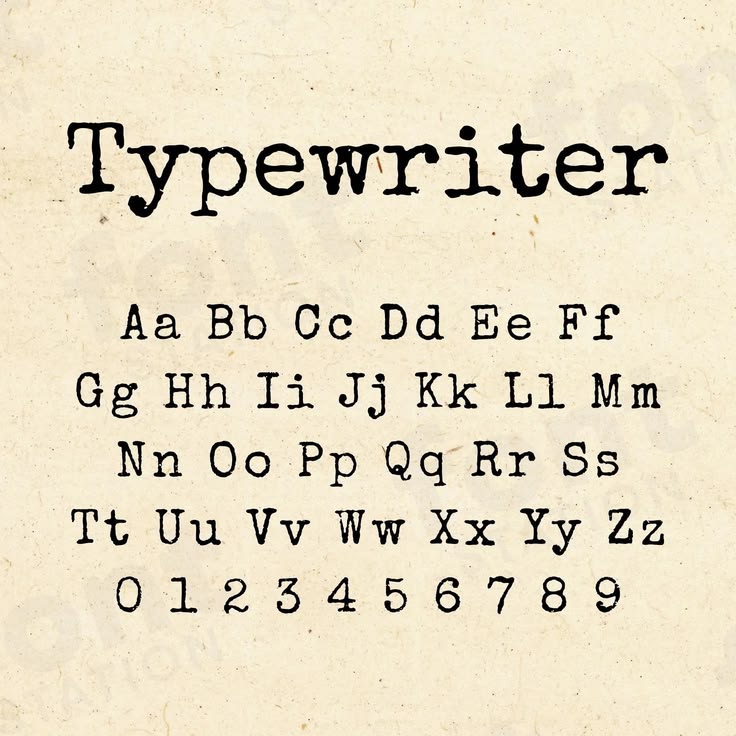
Font chữ Typewriter
Font chữ Typewriter (hay còn gọi là font máy đánh chữ, font chữ đánh máy ngày xưa) là nhóm kiểu chữ mô phỏng các ký tự được tạo ra từ máy đánh chữ cơ học. Đặc trưng của font là nét chữ đơn giản, khoảng cách ký tự đều và mang đậm phong cách cổ điển, tạo cảm giác hoài niệm cho các thiết kế.
Ngày nay, font Typewriter được ứng dụng rộng rãi trong thiết kế poster, bìa sách, bao bì, menu, thiệp và nhiều ấn phẩm truyền thông. Bên cạnh các font kinh điển, hiện nay cũng có nhiều font Typewriter Việt hóa hỗ trợ đầy đủ dấu tiếng Việt, giúp designer và doanh nghiệp dễ dàng sử dụng trong các dự án thiết kế và in ấn.
Tổng hợp 10+ font chữ Typewriter Việt hóa đẹp, miễn phí tải về
Nếu bạn đang tìm kiếm font Typewriter Việt hóa miễn phí để thiết kế poster, bao bì, menu hay các ấn phẩm mang phong cách vintage, dưới đây là những font đơn cách hỗ trợ tiếng Việt, được sử dụng miễn phí và phù hợp cho nhiều mục đích thiết kế.
Font Typewriter phong cách cổ điển, retro
- VT323: Lấy cảm hứng từ màn hình máy tính và máy đánh chữ điện tử thập niên 80, phù hợp với các thiết kế retro, pixel và poster hoài cổ.
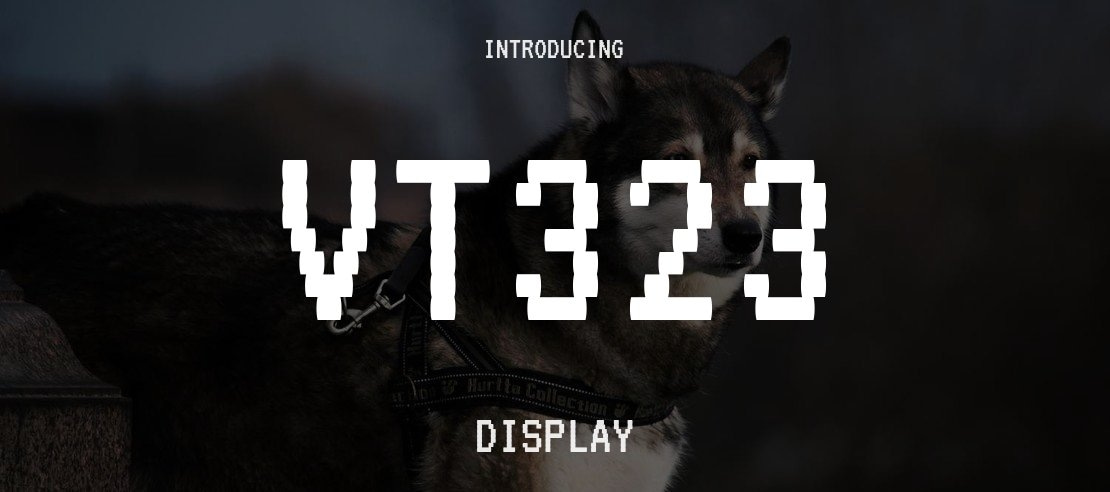
VT323
- Space Mono: Sở hữu nét chữ hơi lệch tự nhiên, mang đậm phong cách máy đánh chữ cổ nhưng vẫn hiện đại, thích hợp cho tiêu đề và ấn phẩm sáng tạo.
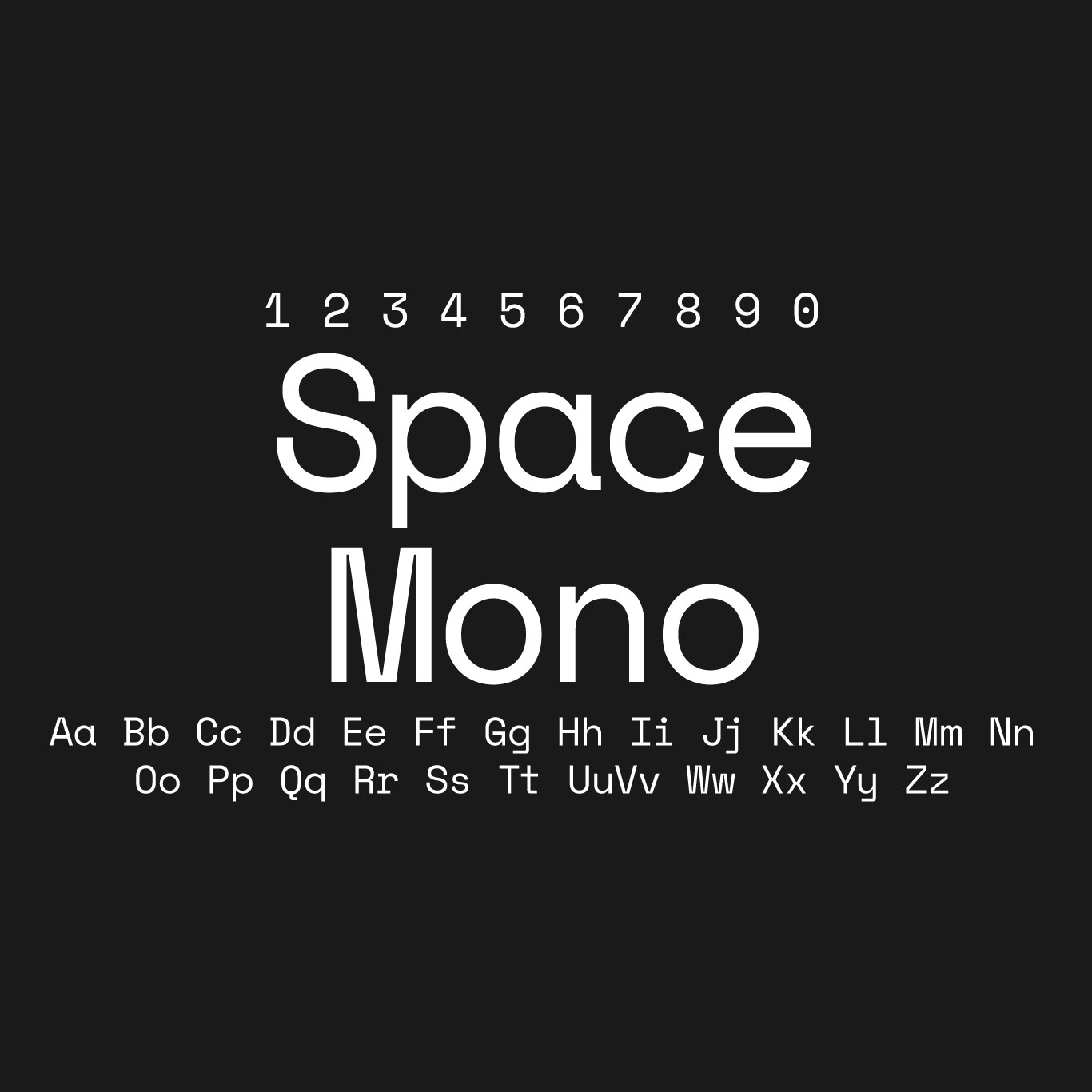
Space Mono
- Cousine: Mô phỏng kiểu chữ Courier truyền thống với các ký tự cân đối, phù hợp cho tài liệu, menu và thiết kế theo phong cách cổ điển.
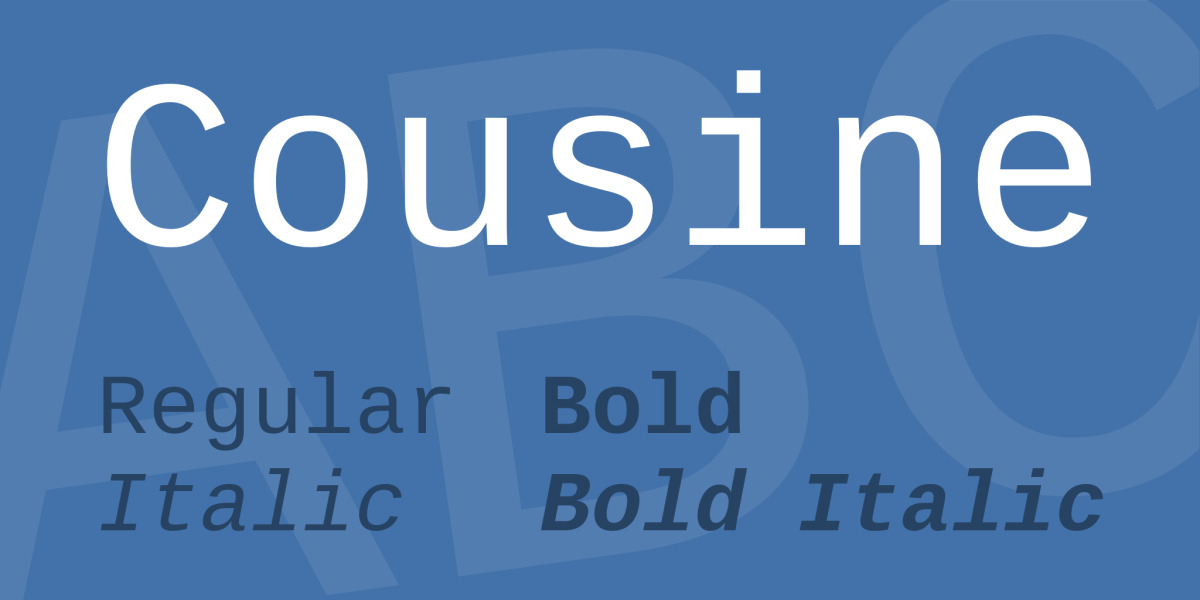
Cousine
- Xanh Mono: Font monospace do người Việt phát triển, hỗ trợ đầy đủ dấu tiếng Việt, thích hợp cho cả nội dung và tiêu đề.
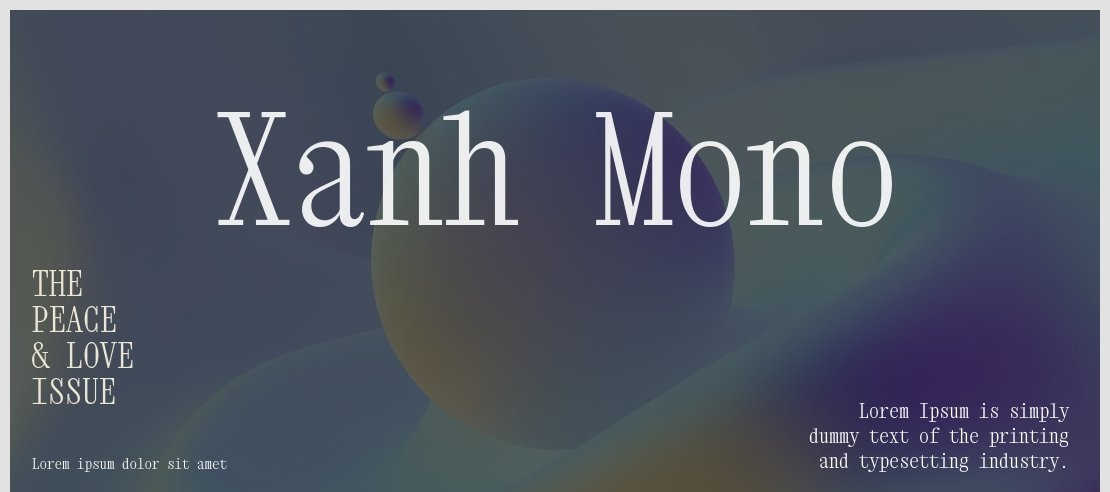
Xanh Mono
- Chivo Mono: Thiết kế vuông vức, khỏe khoắn với hơi hướng retro, phù hợp cho poster, banner và bao bì vintage.
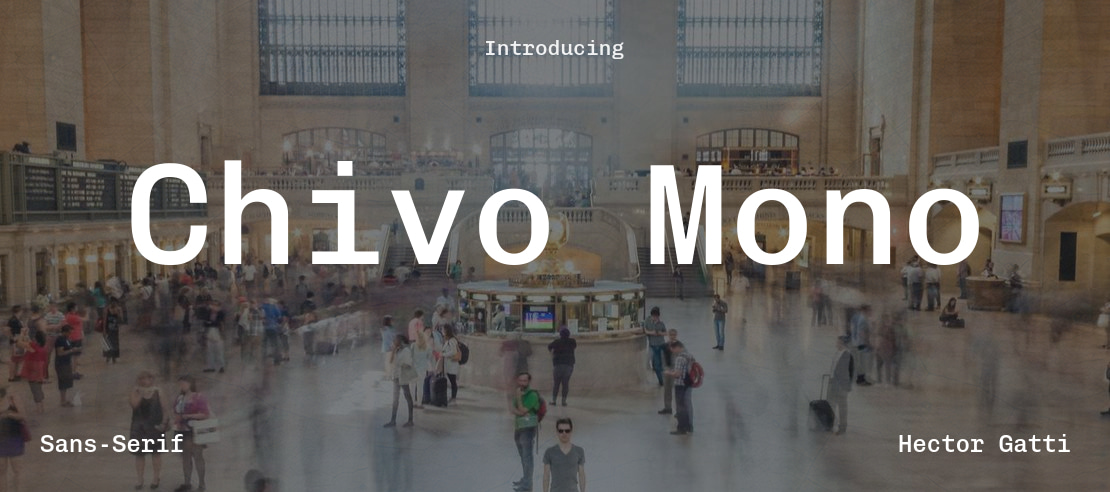
Chivo Mono
- Major Mono Display: Font có cá tính mạnh với toàn bộ ký tự viết hoa, thường được dùng cho logo, tiêu đề hoặc các thiết kế cần tạo điểm nhấn.
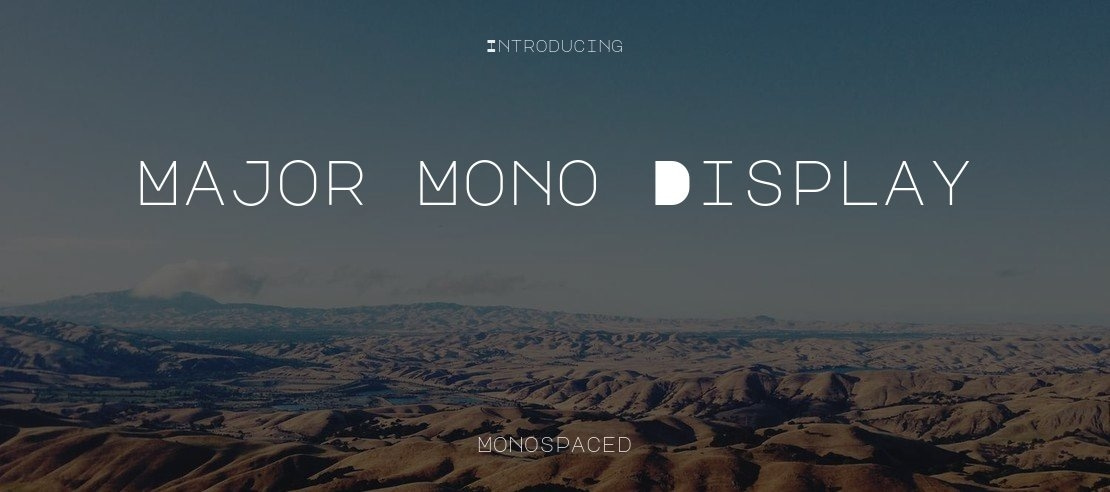
Major Mono Display
Font Mono hiện đại, dễ đọc
- IBM Plex Mono: Thiết kế bởi IBM với kiểu chữ rõ ràng, cân đối, phù hợp cho cả văn bản dài và các thiết kế mang phong cách máy đánh chữ hiện đại.
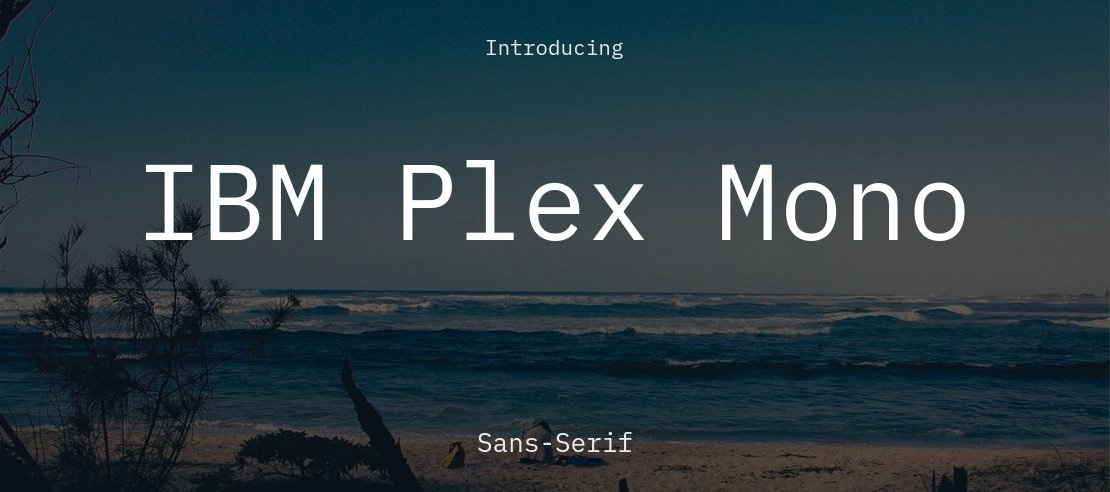
IBM Plex Mono
- JetBrains Mono: Font đơn cách hiện đại, hiển thị sắc nét và dễ đọc, phù hợp cho giao diện, tài liệu hoặc thiết kế tối giản.
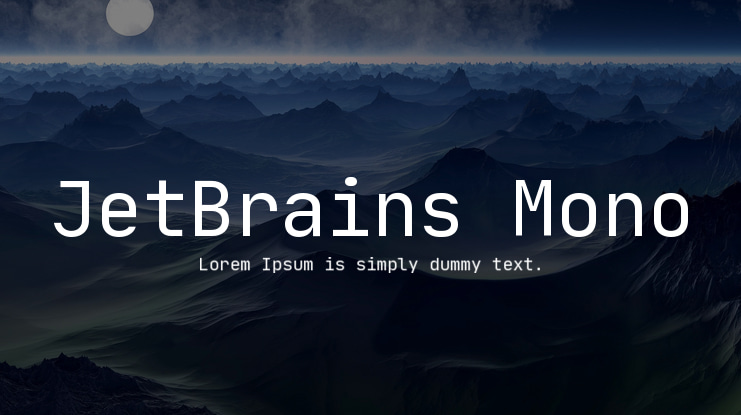
JetBrains Mono
- Source Code Pro: Font miễn phí của Adobe với khoảng cách ký tự hợp lý, thích hợp cho các ấn phẩm cần sự gọn gàng và chuyên nghiệp.
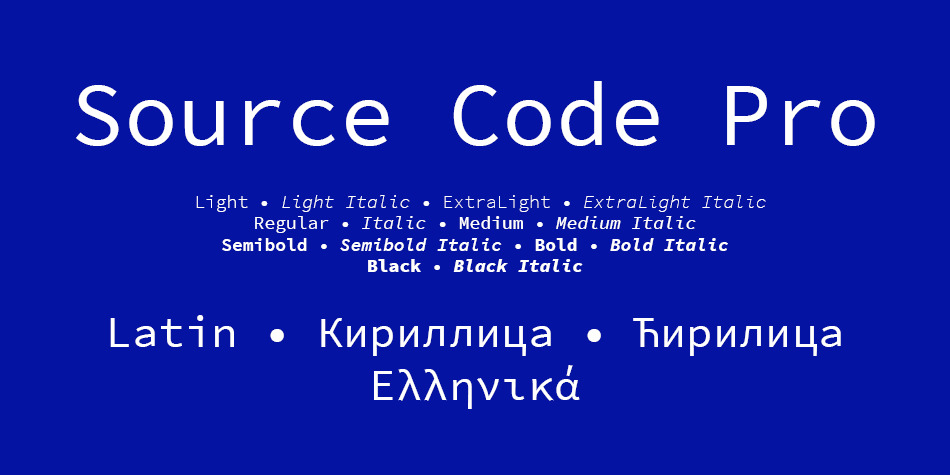
Source Code Pro
- Roboto Mono: Thuộc họ Roboto quen thuộc, mang phong cách hiện đại, dễ phối với nhiều kiểu font khác trong cùng một thiết kế.
Roboto Mono
- Overpass Mono: Nét chữ thanh thoát, đơn giản và dễ đọc, phù hợp cho brochure, catalogue hoặc các thiết kế mang phong cách tối giản.
Overpass Mono
- Cascadia Mono: Font monospace của Microsoft với khoảng cách ký tự thoáng, hỗ trợ hiển thị tốt trên cả màn hình và các ấn phẩm in.
Cascadia Mono
Font Typewriter phù hợp với những phong cách thiết kế nào?
Font Typewriter mang vẻ đẹp hoài cổ, mộc mạc và chân thực nên được ứng dụng trong nhiều phong cách thiết kế khác nhau. Tùy vào cách phối màu, hình ảnh và bố cục, kiểu chữ này có thể tạo nên những ấn tượng rất riêng cho từng dự án.
Font Typewriter phù hợp với những phong cách
- Vintage: Gợi nhớ những thập niên cũ, phù hợp với poster, bìa sách, quán cà phê hoặc cửa hàng theo phong cách cổ điển.
- Retro: Kết hợp cùng bảng màu nổi bật và hình khối đặc trưng để tạo nên các thiết kế mang hơi thở của những năm 70–90.
- Rustic & Handmade: Thích hợp cho bao bì thủ công, tem nhãn sản phẩm, thiệp cảm ơn và các thương hiệu đề cao sự mộc mạc, gần gũi.
- Editorial & Newspaper: Tái hiện phong cách báo chí, tài liệu và bản thảo cũ, thường được sử dụng cho bìa sách, tạp chí hoặc ấn phẩm truyền thông.
- Minimal Vintage: Phối cùng các font Sans Serif hiện đại để tạo nên thiết kế tối giản nhưng vẫn giữ nét hoài niệm, phù hợp với logo, menu và nhận diện thương hiệu.
So sánh các font Typewriter phổ biến
Mỗi font Typewriter đều có phong cách và mục đích sử dụng khác nhau. Bảng dưới đây sẽ giúp bạn dễ dàng lựa chọn font phù hợp với nhu cầu thiết kế.